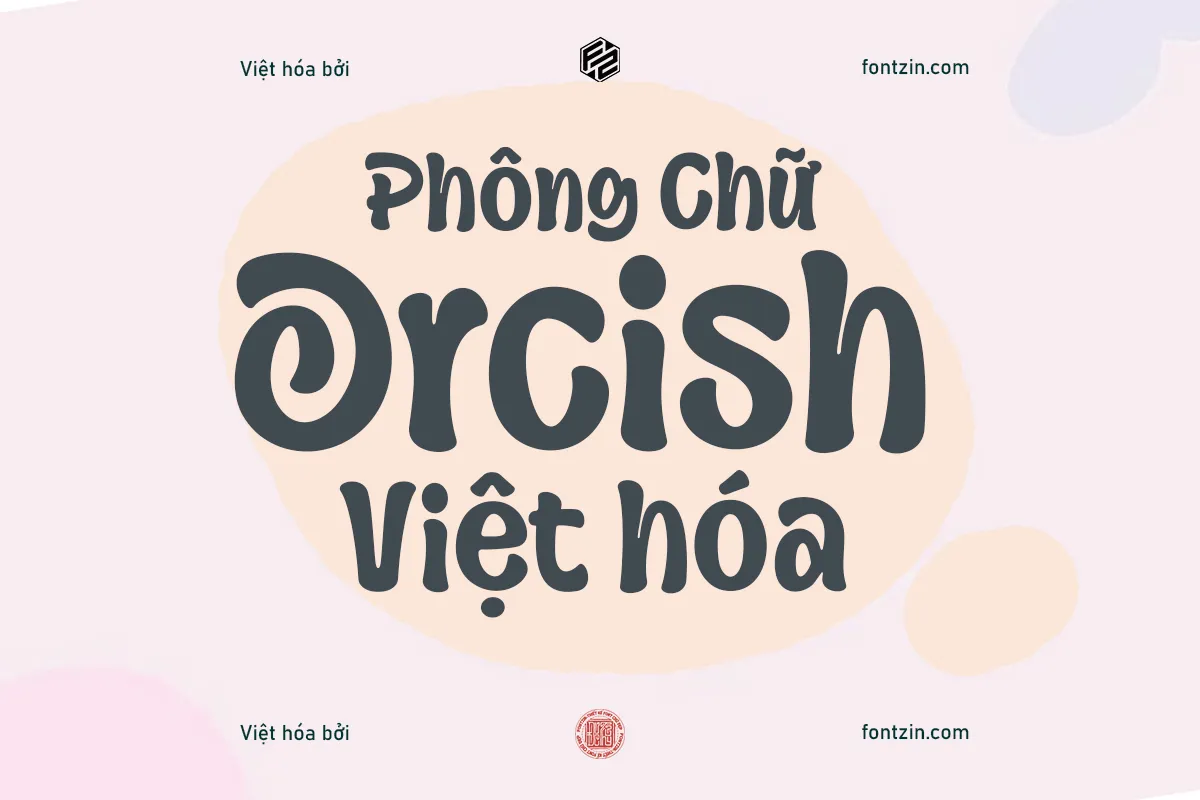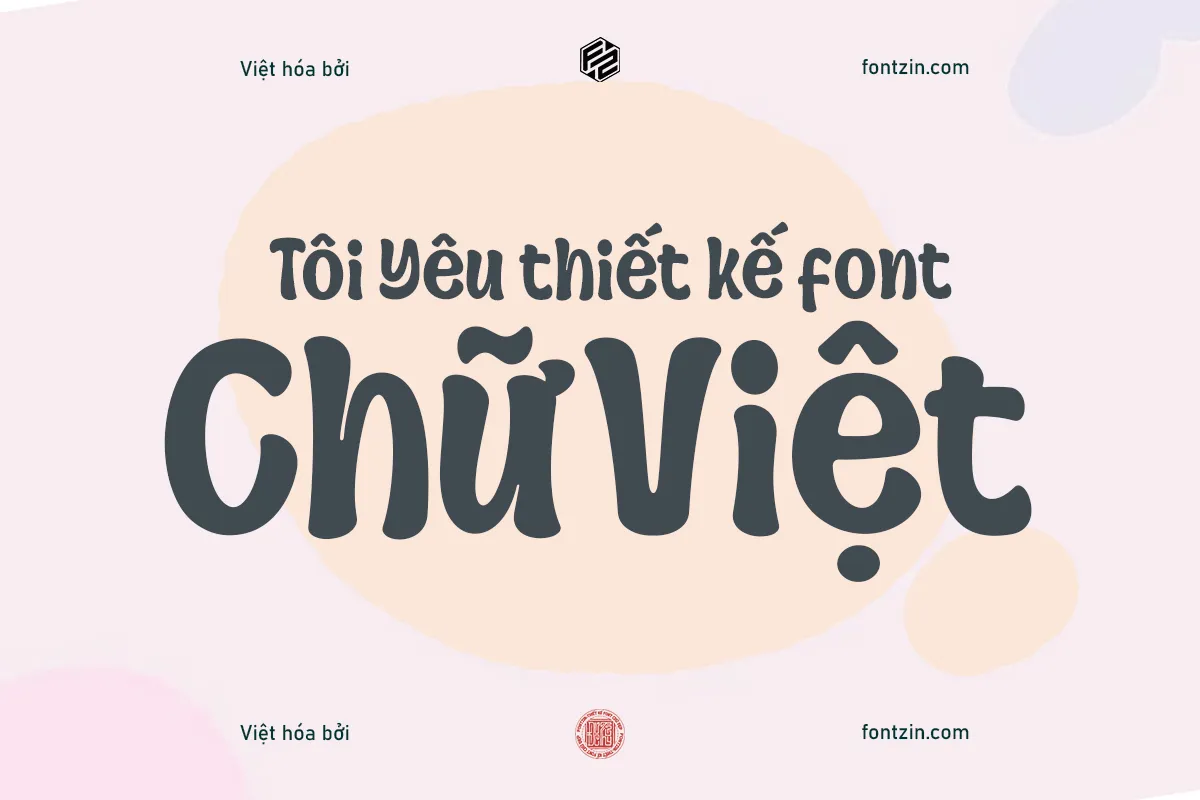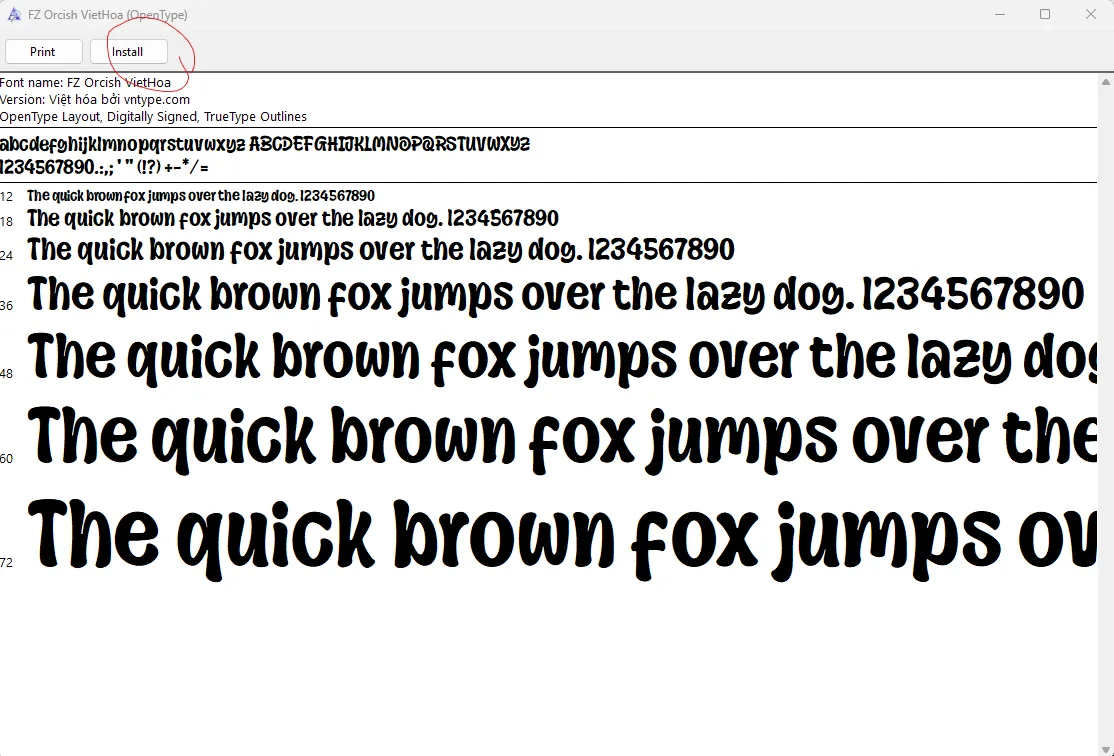
Orcish font Việt hóa là phiên bản font Orcish đã được bổ sung đầy đủ bộ ký tự tiếng Việt, giúp người dùng dễ dàng thiết kế tiêu đề, poster, bao bì, logo và nội dung mạng xã hội mang phong cách cá tính.
Với hình dáng chữ mềm mại nhưng khác biệt, Orcish tạo cảm giác vui nhộn, thủ công và nổi bật ngay từ cái nhìn đầu tiên. Phiên bản font này được thực hiện bởi Đức Thủy, giúp người dùng Việt Nam sử dụng font thuận tiện hơn mà không gặp lỗi dấu hoặc thiếu ký tự khi gõ tiếng Việt.
Orcish font Việt hóa có gì đặc biệt?
Orcish là kiểu chữ display mang tinh thần sáng tạo và giàu cá tính. Font sử dụng các đường cong độc đáo, hình dáng ký tự có phần vui mắt và tạo cảm giác gần gũi như chữ viết thủ công.
Bản Orcish font Việt hóa được bổ sung các ký tự tiếng Việt cần thiết, bao gồm:
- Các nguyên âm có dấu như à, á, ả, ã, ạ.
- Các nhóm ký tự â, ă, ê, ô, ơ và ư.
- Đầy đủ dấu thanh và dấu phụ trong tiếng Việt.
- Chữ hoa, chữ thường, chữ số và các ký tự cơ bản.
Phong cách thiết kế của font Orcish
Điểm mạnh của Orcish nằm ở khả năng tạo sự chú ý. Font phù hợp với những thiết kế cần cảm giác trẻ trung, thủ công và có dấu ấn riêng. Các đường nét bo tròn kết hợp với hình dáng ký tự phá cách giúp văn bản trở nên sinh động hơn so với các font chữ thông thường.
Bạn có thể dùng font Orcish Việt hóa cho:
- Thiết kế logo và nhận diện thương hiệu cá nhân.
- Poster, banner hoặc ảnh quảng cáo trên mạng xã hội.
- Nhãn sản phẩm, bao bì đồ handmade và sản phẩm dành cho trẻ em.
- Tiêu đề truyện tranh, video, thumbnail và nội dung giải trí.
- Thiệp, sticker, áo thun và các sản phẩm in ấn sáng tạo.
Orcish phù hợp nhất khi sử dụng ở kích thước lớn. Với đoạn văn dài hoặc nội dung cần đọc nhanh, bạn nên kết hợp font này với một font sans serif đơn giản để tạo sự cân bằng.
Gợi ý sử dụng Orcish font Việt hóa
Để font phát huy hiệu quả, hãy dùng Orcish cho tiêu đề chính hoặc một cụm từ ngắn thay vì sử dụng cho toàn bộ bài viết. Màu sắc tương phản cao, nền đơn giản và khoảng cách chữ hợp lý sẽ giúp các ký tự đặc trưng của font được thể hiện rõ hơn.
Một số cách phối hợp font
- Orcish cho tiêu đề, font sans serif cho phần mô tả.
- Chữ Orcish màu đậm trên nền sáng khi thiết kế bao bì.
- Dùng hiệu ứng đổ bóng nhẹ cho poster hoặc thumbnail.
- Kết hợp màu kem, cam, nâu hoặc xanh lá để nhấn mạnh cảm giác thủ công.